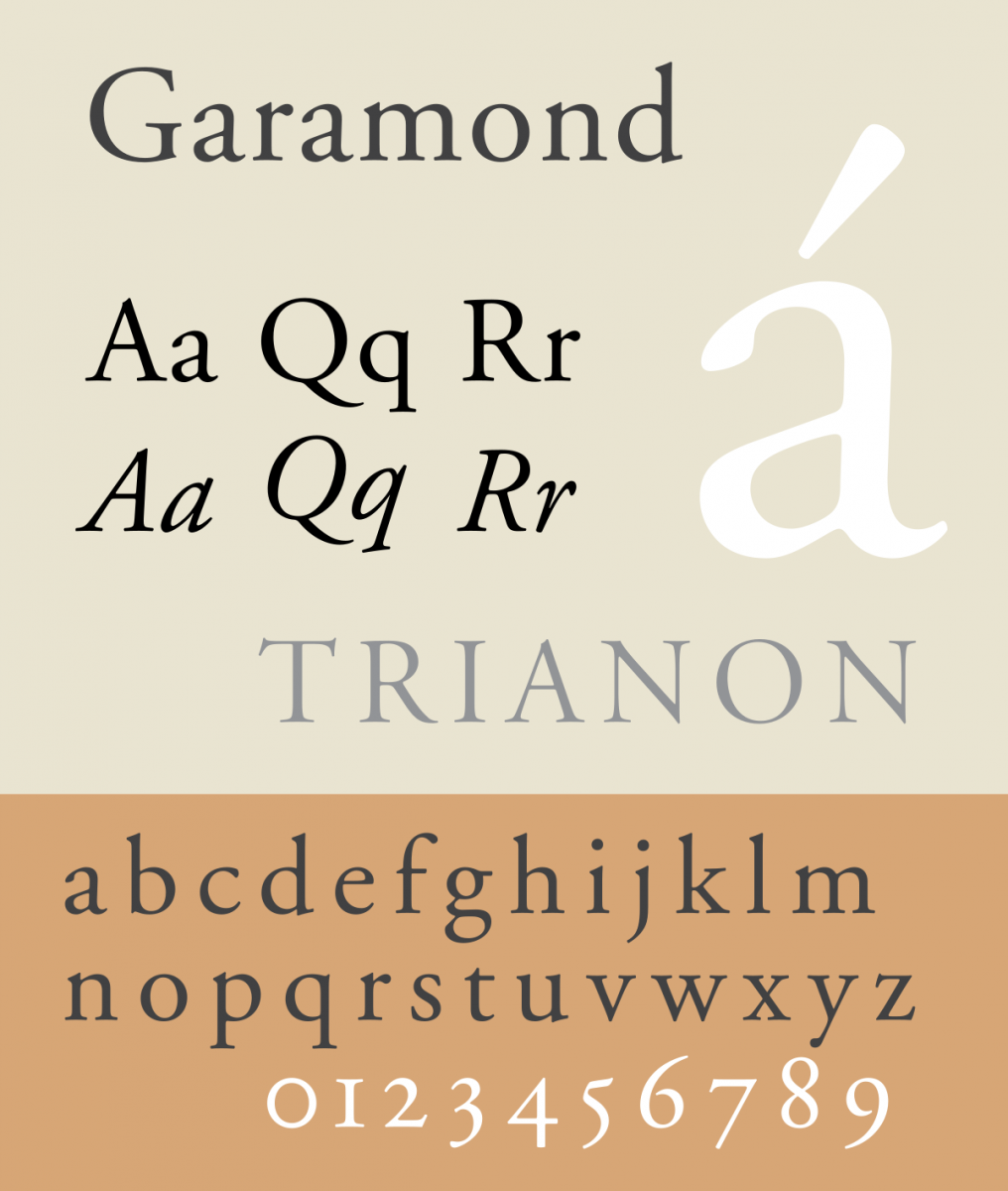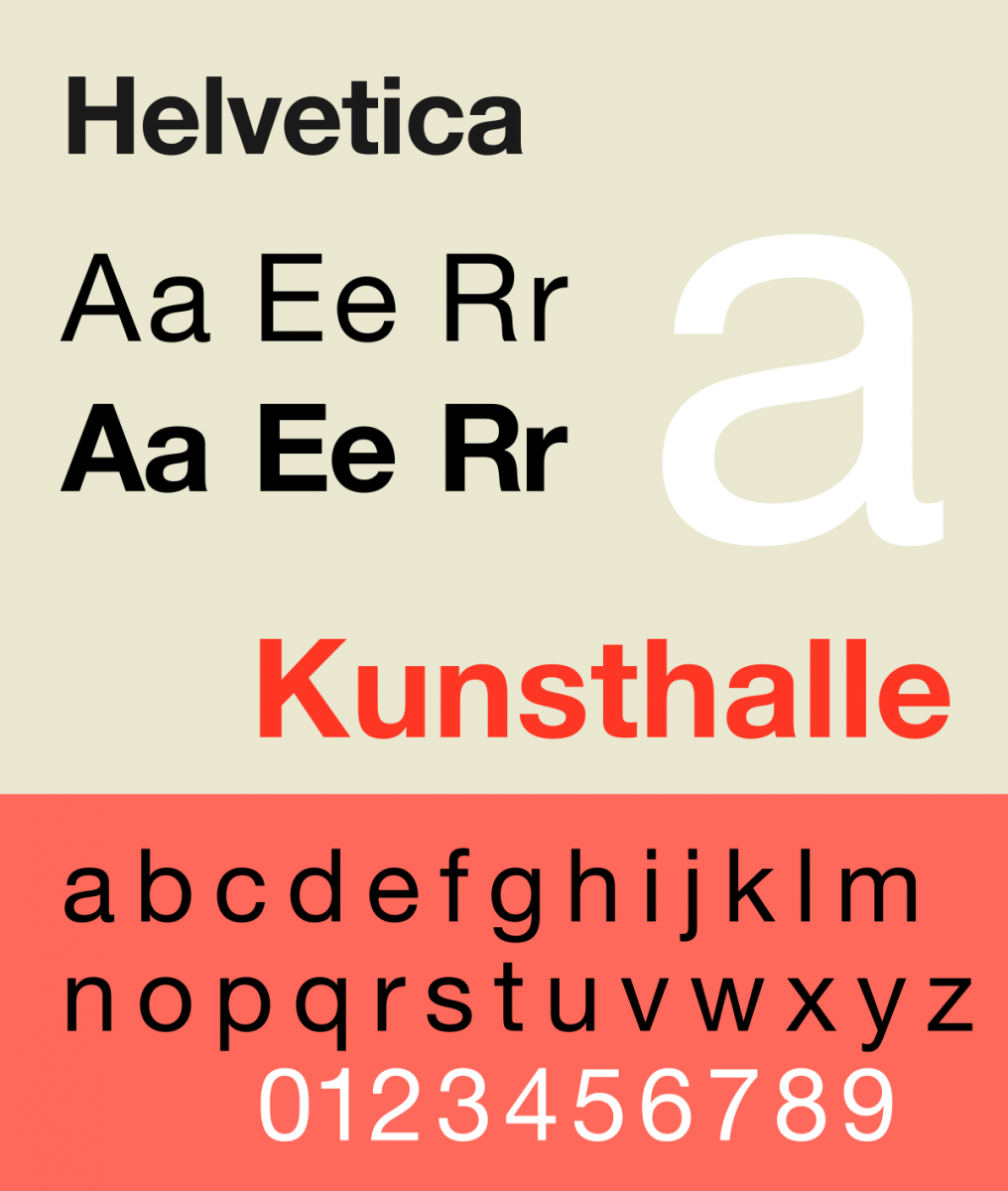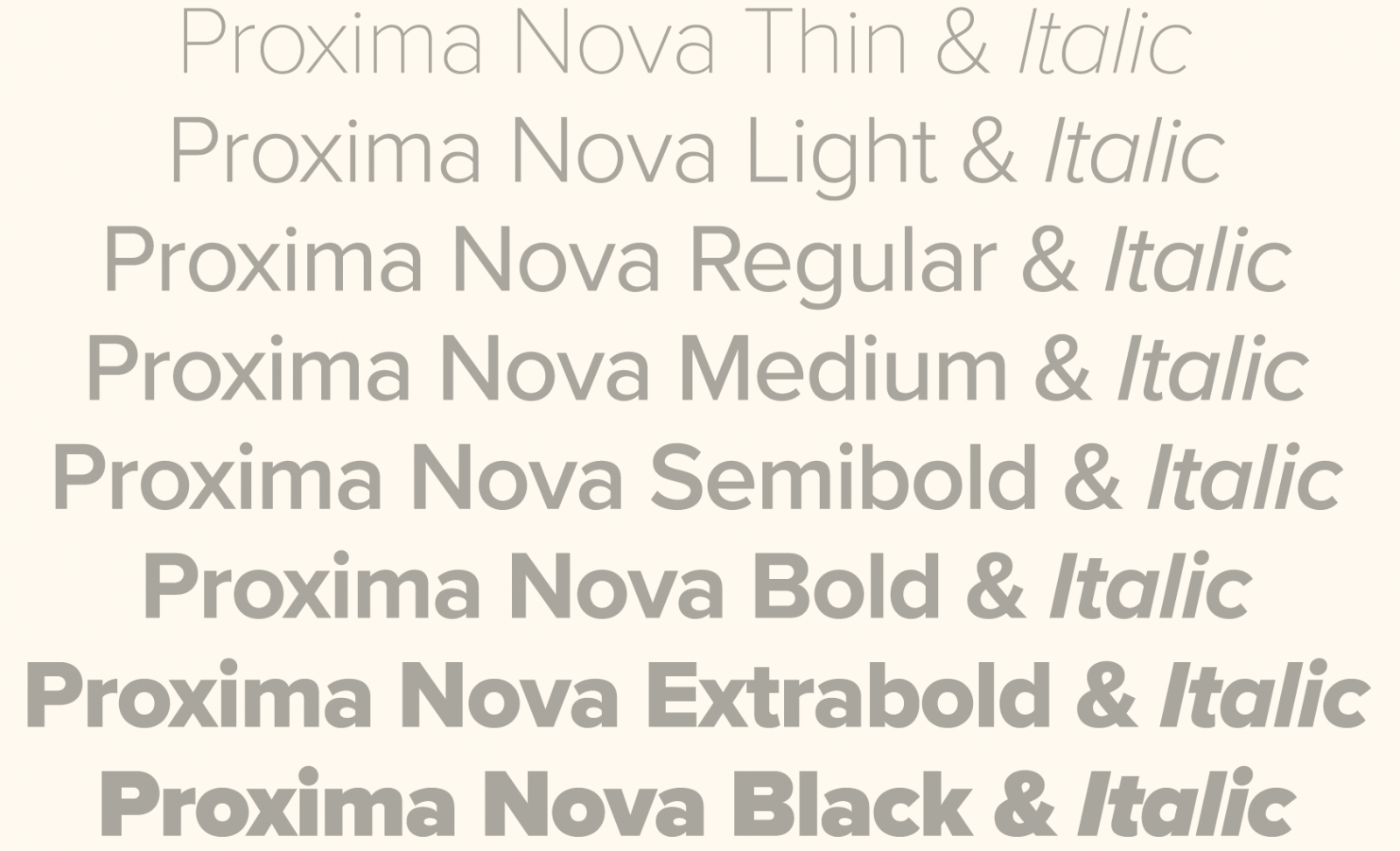
打工仔想揾份好工作,除了CV要寫亮麗之外,字體選擇亦十分重要,選用合適的字體撰寫履歷表,能向僱主或招聘人員留下好的印象。然而,哪些字型比較適合呢?Artfia為你精選出幾款常用字體作比較。
《彭博商業周刊》早前向設計師進行了訪問,以下是設計師們推介的英文字體。
1. 最佳英文字體:Helvetica
設計師Brian Hoff指出「Helvetica」是最佳的CV字體。
Helvetica是一種廣泛使用於拉丁字母的無襯線字體,是瑞士設計師馬克斯·米丁格(Max Miedinger)和愛德華·霍夫曼(Eduard Hoffmann)於1957年設計的。
Helvetica字體給人穩重、得體、專業和誠懇的感覺,特別適合專業人仕。
2. 較佳英文字體
設計師亦建議「Proxima Nova」,它的字體看起來較圓潤,故頗受白領歡迎。
「Garamond」字體亦在可選之列,它字型清晰,眼睛容易跟上。若你喜歡高貴、秀麗的字體,「Garamond」絕對是你的首選。
「Didot」則特別適合時尚行業,它字體高挑,能引起想像,還帶點女性味道。設計師Luckhurst指,這個字體就像穿上黑裙到舞會般。
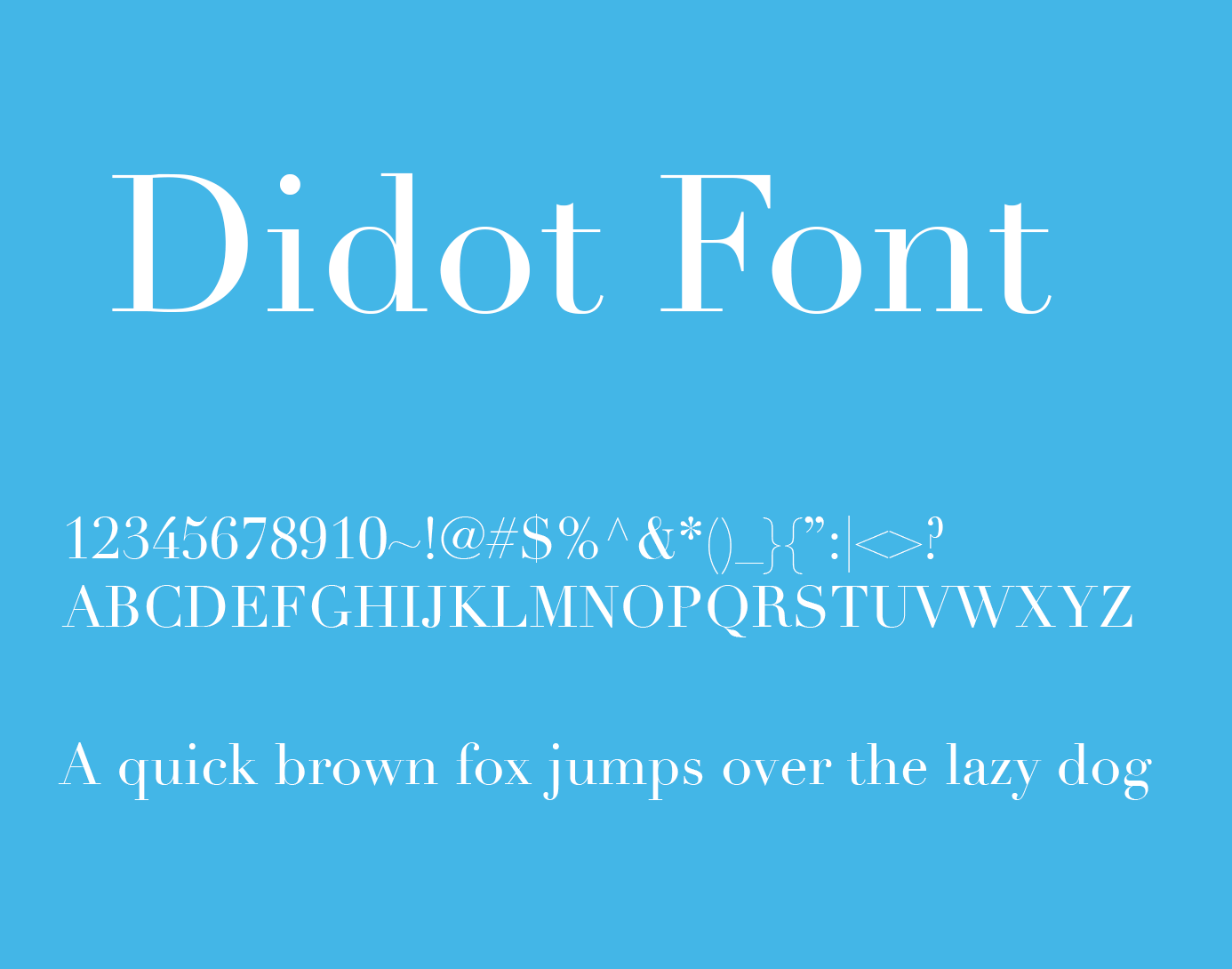
3. 較差字體:Times New Roman
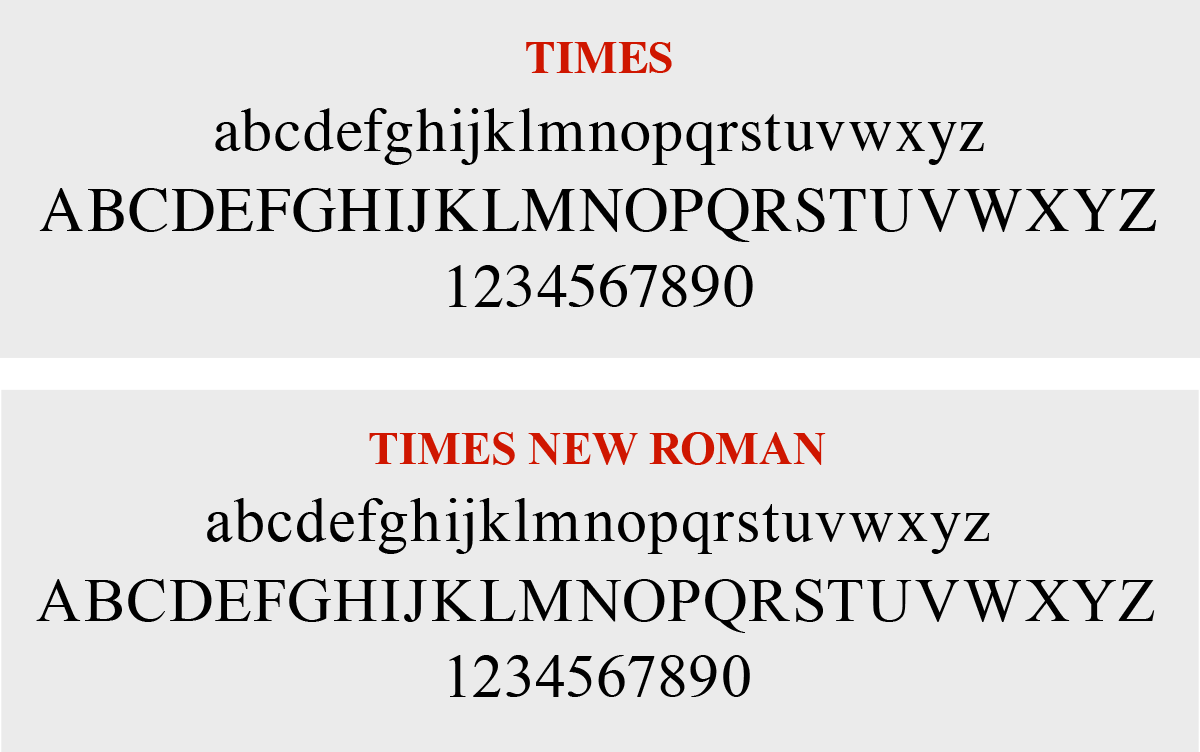
而「Times New Roman」則是一個很較差的選擇。德國字型設計師Martina Flor解釋,「Times New Roman」本身沒有問題,不過由於此字體沿用多年,當老闆看到使用「Times New Roman」求職信時,可能會覺得你沒有誠意,予人一種懶散的感覺。
除此以外,撰寫求職信時,切記不要選擇「Courier」字體。「Courier」字體模仿打字機的字體,但相信在這個年代大家都沒有打字機,因此求職者也不需要假裝自己有一部。